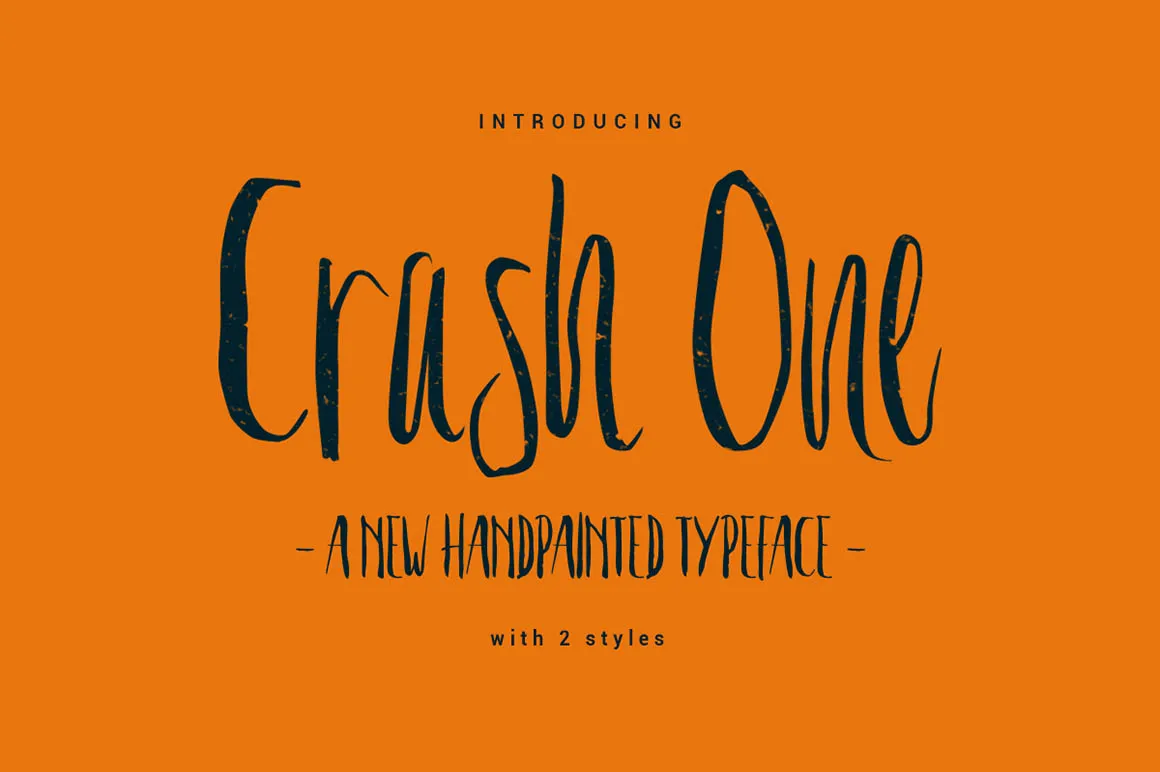
Olha aqui! Estou aí uma nova mão-duração! Eu gostaria de apresentar vocês a Crash One Typeface, uma tipografia escrita à mão que promete ser adorada por todos os amantes do design. Este é um tipo exclusivo e atual, feito para se destacar em qualquer projeto impresso ou digital. Introduzimos Crash One Typeface! Desenhado e compartilhado pelo Pathero Studio. Esta fonte brush é única e trendy. Ela brilha nas suas campanhas de marca, logotipos, cartões-postais, frases memoráveis e qualquer projeto incrível que esteja por vir. Crash One conta com caracteres normais, minúsculas, maiúsculas, números, pontuação, ligações e caracteres internacionais. Este tipo é perfeito para adicionar um toque único a seus projetos de design gráfico, criando uma identidade visual forte e imersiva. Estamos ansiosos para ver vocês experimentando com ela! Não se esqueça de baixar seu Crash One Typeface agora e explore todos os recursos desta fonte cheia de personalidade.